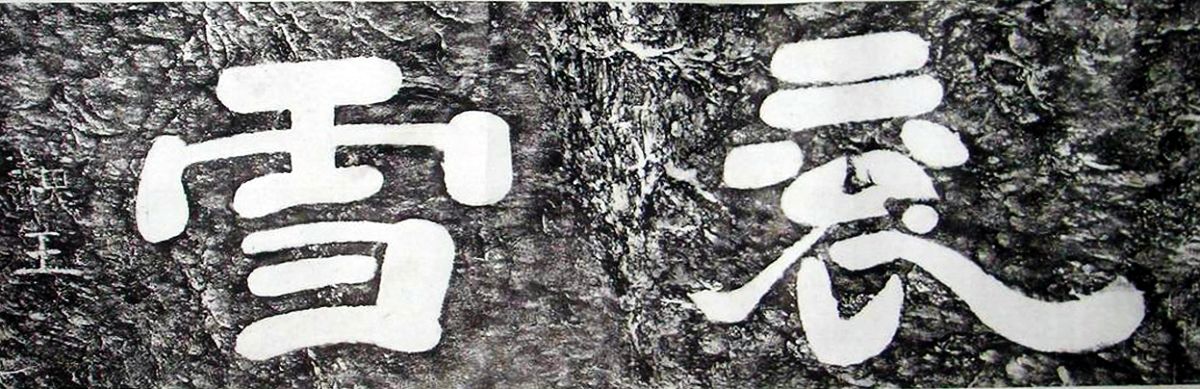
曹操(传) 《衮雪》 陕西汉中市博物馆藏
“衮雪”——褒谷摩崖石刻十三品之第一品,书体为汉隶大字。刻石原在褒斜栈道南端重要的隘口——褒谷口,褒水中巨大的皛石上,摩崖石刻整体呈长方形,宽148厘米,高67厘米,字径35~46厘米。
曹操是个卓越的政治家、思想家、文学家,在书法上也有独到成就。晋代陆云给陆机的信中说“曹公藏石墨数十万斤”。传为曹操唯一书法为“衮雪”二字,据《三国志·魏书·武帝纪》载,建安二十年(215年),曹操曾于建安二十年(公元215年)和二十四年(公元219年)两次来到汉中,相传曾登临褒谷故地,一览大好河山。见石门外幽谷深滩中,石多浪激,飞流奔泻,银涛做窝,犹如白雪翻滚时,豪情难仰挥毫即书隶体“衮雪”二字于谷中石尖,以喻褒谷山水之美。飘逸俊挺的字迹,不仅表现了褒谷博大的气势,更显示了魏武帝宏阔的气魄与壮志。
此石现存陕西汉中市博物馆,后人因慕其名,又在“衮雪”二字左侧追镌“魏王”两个小字已示区别。“衮”字一撇一捺颇有动态之感,“雪”字则有静态质感。然而,很多学者认为这件书迹不过是后代的好事者所伪造,我们可以看出“衮雪”二字的笔画,是由一个习惯於楷书写法的人所作的隶书,而曹操的时代楷书并未成熟,不应该有这种情形,由此可见它绝非曹操的书迹。
曹操性格豪爽、气度非凡。他不仅有盖世之才,纳贤之德,而且长与军事,善于书法,乐观进取,可谓文武双全。